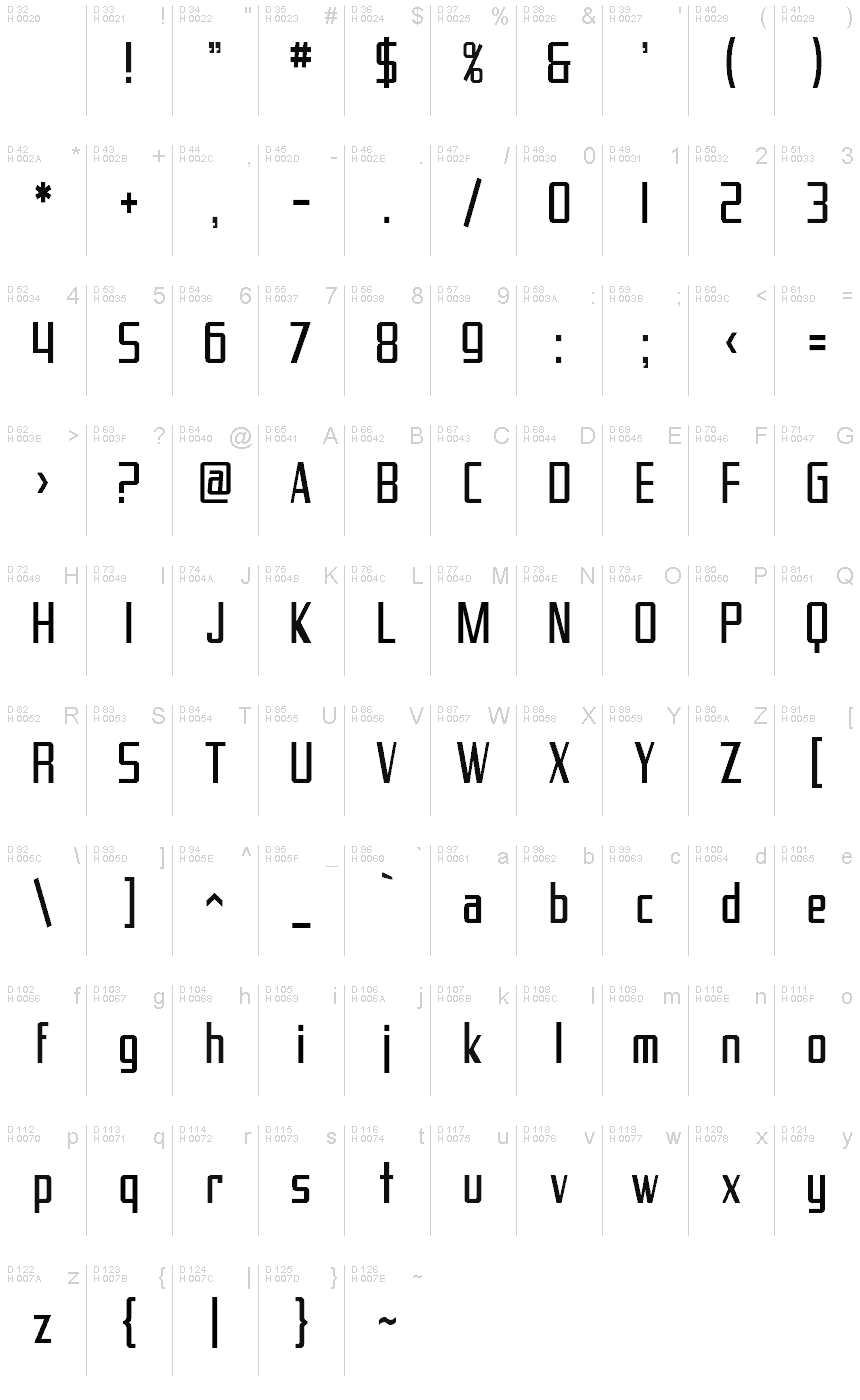
SF Proverbial Gothic Condensed
SF Proverbial Gothic Condensed nasce dalla famiglia SF Proverbial Gothic con un aspetto elegante e moderno. Progettato da ShyFonts Type Foundry, questo font display incarna l'essenza dello stile techno contemporaneo, mentre il suo peso semi-light armonizza forza ed eleganza. La larghezza extra condensata di questo font non solo garantisce un uso efficiente dello spazio, ma conferisce anche un senso di sofisticatezza e chiarezza visivamente accattivante.
La geometria lineare e le linee pulite si prestano a una vasta gamma di applicazioni creative, rendendolo perfetto per startup tecnologiche, branding nel settore moda o qualsiasi progetto che desideri un tocco di minimalismo futuristico. SF Proverbial Gothic Condensed si distingue per la sua estetica curata, in grado di dare vita a titoli, loghi e qualsiasi spazio in cui una tipografia di grande impatto sia fondamentale. La versatilità e lo stile di questo font lo rendono uno strumento indispensabile per i designer che mirano a creare narrazioni visive avvincenti.